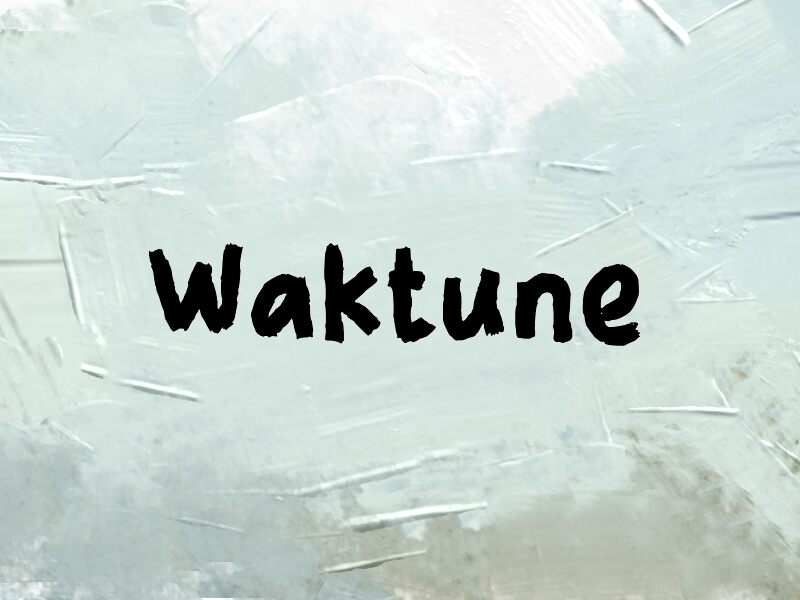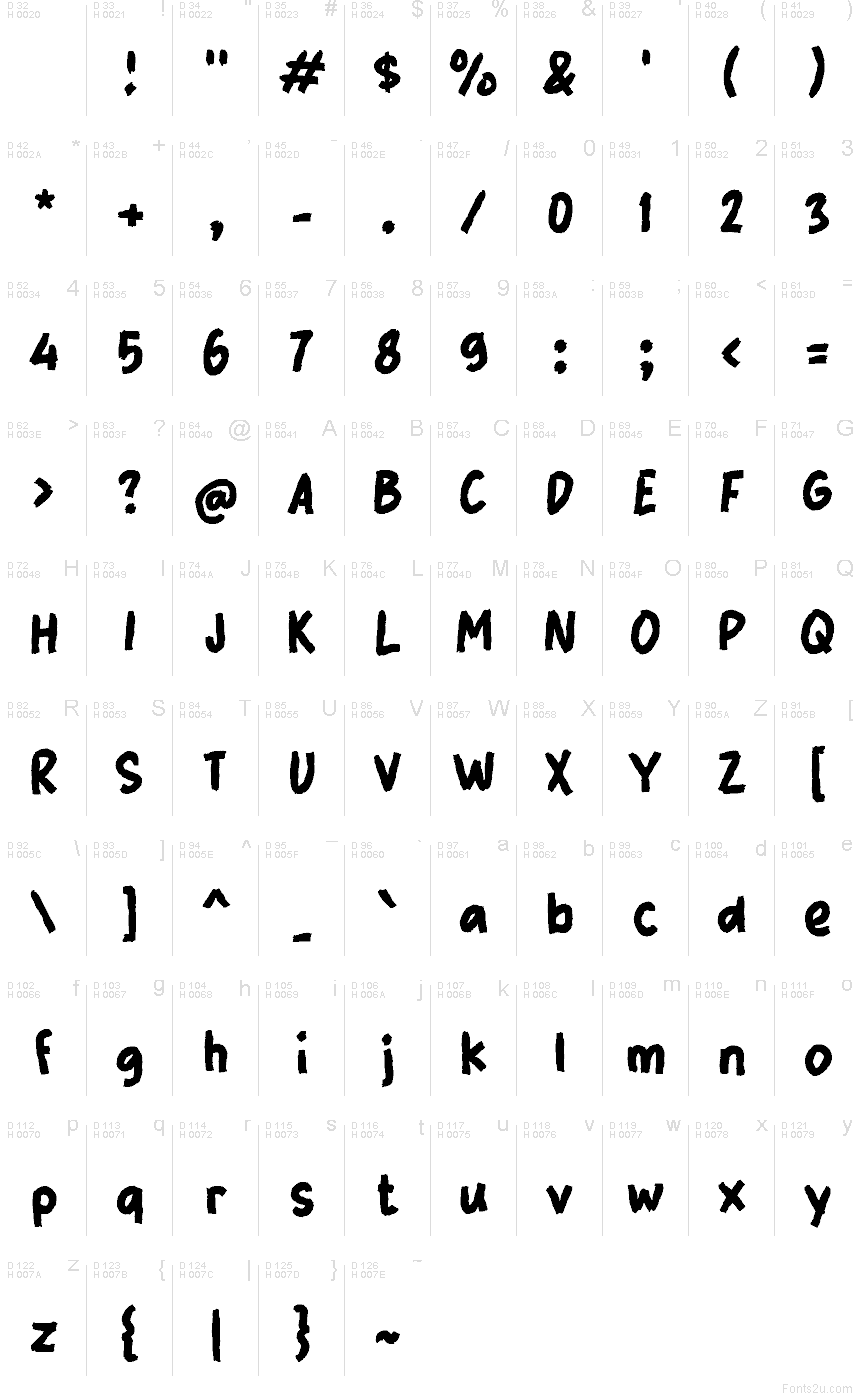
Waktune od Wep je bezplatné bezpatkové písmo typu brush, které vyniká svou drsnou texturou s efektem štětin, díky níž mají písmena zubaté okraje a lehce nepravidelné tahy. Povrch připomínající zaschlou barvu mu dodává atmosféru rychlého plakátového nápisu místo hladké kaligrafie, a díky pevnému, vzpřímenému rytmu působí tvary písmen přímočaře a syrově.
Skvěle funguje na hudebních letácích, streetwearových grafikách, plakátech na akce, náhledech videí na YouTube nebo merchandisingu, kde tato textura škrábaného štětce dodává vizuální šmrnc. Písmo nejlépe vynikne v krátkých nadpisech a titulech, protože jeho syrový, ručně malovaný vzhled dodá každému textu okamžitou dominanci, aniž by působil příliš uhlazeně.
Waktune
Prezentace a vizuální ukázka písma Waktune